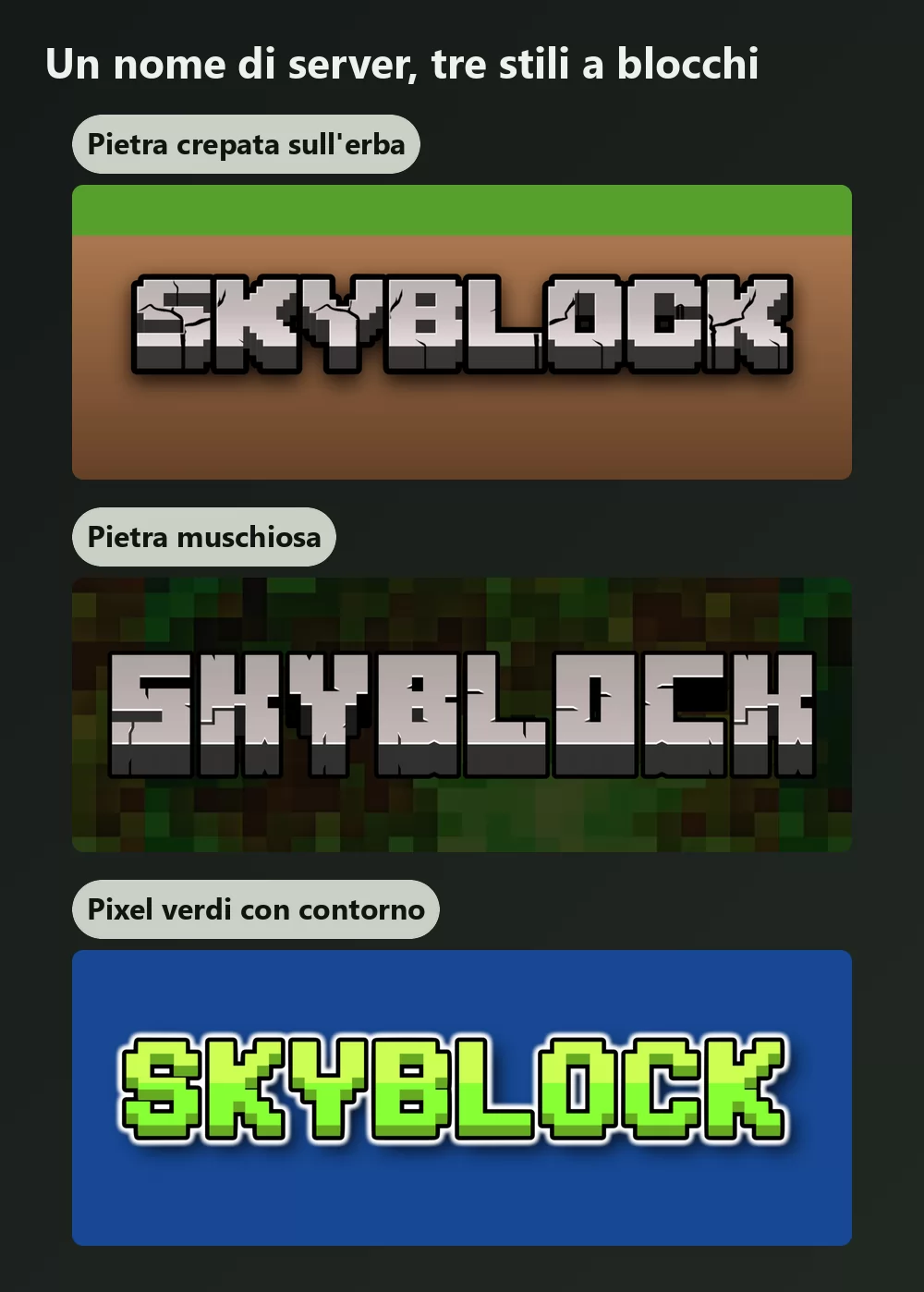
Scrivi «font Minecraft» in un motore di ricerca e ottieni due gruppi di risultati che si contraddicono. Uno propone un carattere a pixel tutto piatto. L'altro propone grosse lettere di pietra percorse da crepe. Entrambi si presentano come il font di Minecraft.
Hanno ragione tutti e due, perché Minecraft usa due caratteri completamente diversi, e il gioco ne distribuisce uno solo. Quasi tutti quelli che cercano hanno in mente il secondo.
La risposta breve: sono due font, non uno
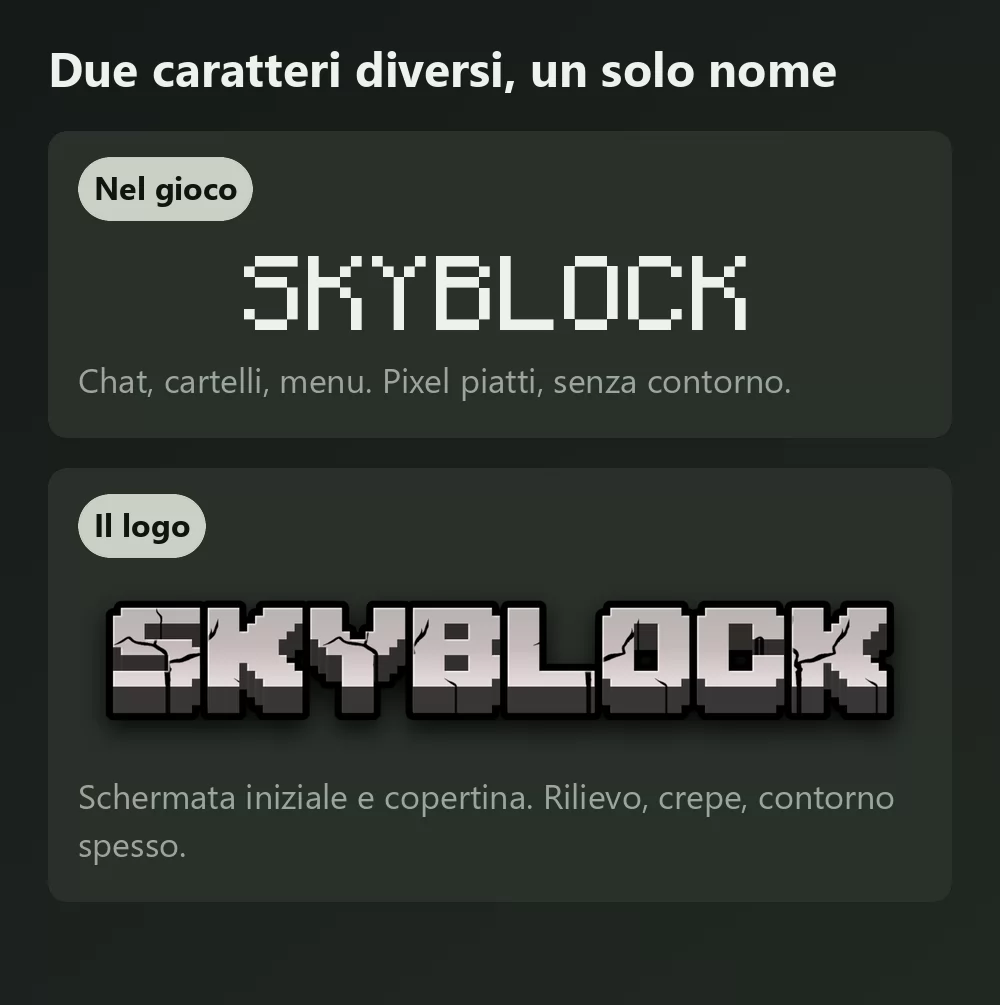
Mojangles è quello su cui gira il gioco. È il piccolo carattere a pixel della chat, dei nomi degli oggetti, dei cartelli, dei menu e di tutti i tabelloni che hai strizzato gli occhi per leggere. Piatto, senza ombreggiatura, senza contorno.
Il carattere del logo è il grosso lettering scolpito nella pietra della schermata iniziale e della copertina. Ha rilievo, un pesante contorno scuro e crepe che attraversano le lettere. Nel gioco non esiste affatto come carattere: è un'illustrazione.
Se stai preparando un banner per un server, una miniatura YouTube, un logo per un SMP o un'intestazione Discord, ti serve il secondo. Se ricostruisci un messaggio di chat o un cartello, ti serve il primo.
Da dove viene davvero Mojangles
Questa parte è una curiosità che vale, e la maggior parte delle pagine la sbaglia.
Mojangles è più vecchio di Minecraft. Markus Persson lo disegnò nel 2001 per un suo gioco precedente, Legend of the Chambered, otto anni prima che Minecraft esistesse, e lo basò sul carattere a pixel 8 x 8 integrato nella scheda grafica IBM EGA del 1984. Il carattere che associ al gioco più venduto di sempre ha iniziato la sua vita come set di caratteri hardware delle prime schede grafiche per PC.
Una correzione già che ci siamo, perché ovunque si legge il contrario: Mojangles non è a spaziatura fissa. I suoi glifi sono disegnati su una griglia di 8 pixel, ma le larghezze vanno da 1 a 8 pixel, ed è per questo che una M maiuscola occupa molto più spazio di una i minuscola. Diverse guide molto lette affermano il contrario. Apri un mondo qualsiasi di Minecraft e guarda un cartello: verificarlo richiede due secondi.
Quindi ogni «font Minecraft» scaricabile è la ricostruzione di qualcuno. Va benissimo, e alcune sono ottime. Significa solo che la licenza da rispettare è quella di chi l'ha ricostruito, non quella di Mojang.
I font che puoi davvero scaricare, e cosa permette ciascuno
Monocraft, quello con la licenza pulita
Se vuoi l'aspetto del gioco e vuoi dormire tranquillo, la risposta è questa. Monocraft, di Idrees Hassan, è un font a spaziatura fissa ispirato al carattere dell'interfaccia di Minecraft, pubblicato sotto licenza SIL Open Font 1.1. Vale a dire: libero, uso commerciale incluso, con attribuzione.
È anche il più completo del gruppo: oltre 1.500 glifi che coprono il latino accentato, il cirillico e il greco, più l'alfabeto galattico standard del tavolo degli incantesimi. Viene distribuito in .ttf e .ttc, e l'autore precisa esplicitamente che si tratta di un progetto amatoriale privo di qualsiasi materiale Mojang.
Due cose da sapere. È deliberatamente a spaziatura fissa, a differenza di Mojangles, perché è nato come font da programmazione: le parole lunghe risultano quindi un po' più larghe che nel gioco. E non ha alcun glifo cinese, giapponese o coreano, il che conta se pensavi di comporci testo CJK.
Le ricostruzioni a pixel gratuite
La più scaricata si chiama semplicemente «Minecraft», di Craftron Gaming, ed è vicina ai cinque milioni di download su DaFont. È un file TrueType da 6 KB che riproduce l'aspetto piatto del gioco, e DaFont lo annuncia come 100 % gratuito.
Posso usare il font di Minecraft su prodotti che vendo? La licenza del font e il marchio sono due questioni distinte. Anche con un font a licenza permissiva, il nome «Minecraft» appartiene a Mojang: consulta le sue linee guida sull'uso commerciale prima di vendere qualsiasi cosa.